글로벌 폰트 디자인 및 기술 선도 기업 모노타입(Monotype)이 웹사이트 제작 플랫폼 Wix(윅스)와 전략적 협업을 맺고, 폰트 라이브러리를 대폭 확장했다고 밝혔다. 이번 협업을 통해 추가된 폰트는 Wix 사용자뿐 아니라 독립 창작자와 크리에이티브 에이전시에도 제공된다. Helvetica®, Avenir® 같은 클래식 폰트부터 Recoleta, Kibitz Pro, Aether 등 최신 트렌드를 반영한 폰트까지 폭넓은 스타일을 아우른다. 이를 통해 사용자는 브랜드 비전에 어울리는 웹사이트를 보다 쉽게 구현할 수 있게 되었다.
이번 폰트 확장에는 모노타입의 폰트 디자인 전문가들이 직접 참여해, 비즈니스용부터 창작자 개인 웹사이트까지 다양한 목적에 적합한 폰트를 엄선했다. 그 결과, 전 세계 Wix 사용자들은 고품질 타이포그래피를 바탕으로 브랜드 개성을 효과적으로 표현하고, 독창적인 디지털 아이덴티티를 구축할 수 있게 되었다.
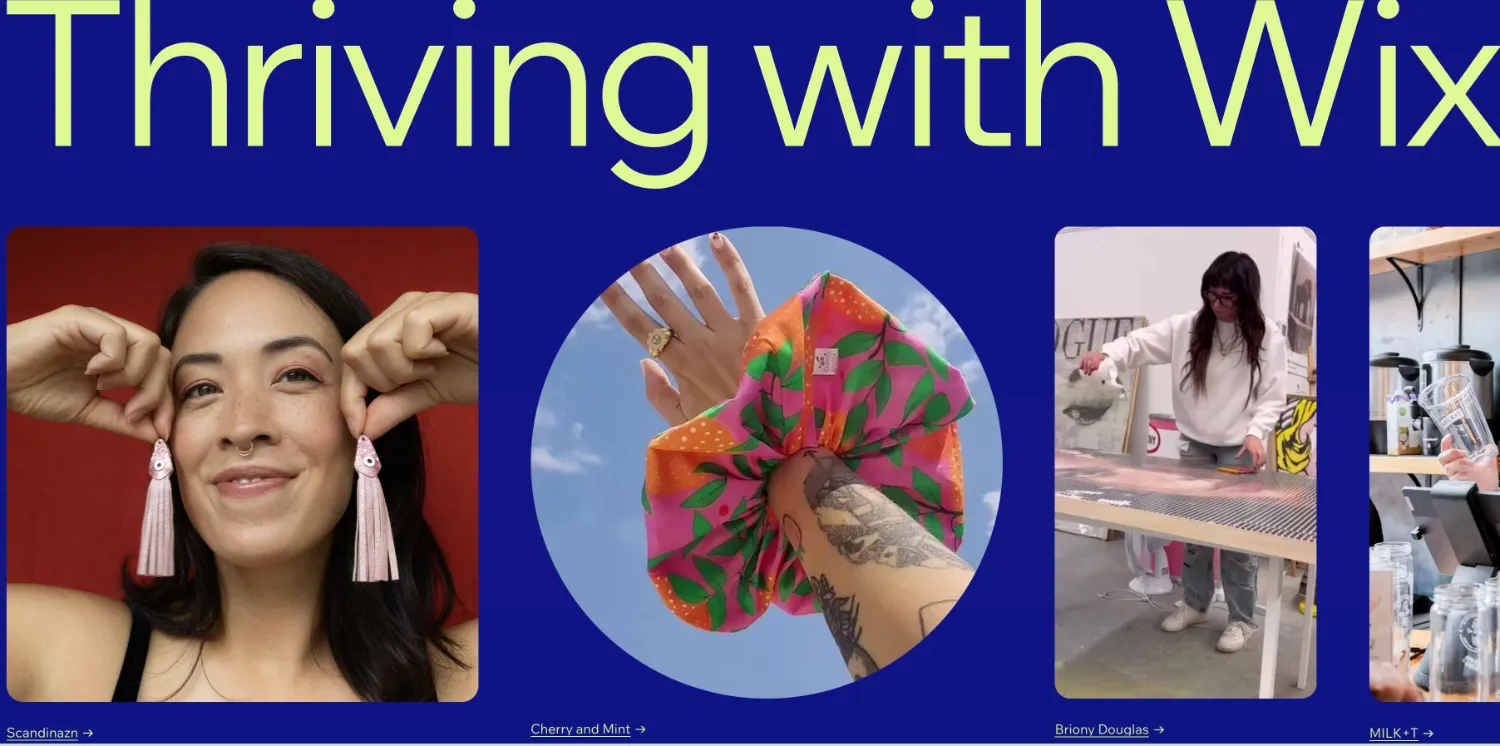
Wix 브랜드 및 디자인 부사장 하깃 카우프만(Hagit Kaufman)은 “폰트는 웹사이트 디자인에서 매우 중요한 요소다. 이번 폰트 라이브러리 확장을 통해 창작자들이 시각적으로 뛰어나고 브랜드에 잘 맞는 웹사이트를 만들 수 있기를 기대한다. 모노타입과의 협업은 전 세계 사용자에게 전문적인 디자인 도구를 꾸준히 제공하겠다는 우리의 의지를 보여주는 사례다”라고 밝혔다.
모노타입 수석 폰트 크리에이티브 디렉터 찰스 닉스(Charles Nix)는 “적절한 폰트는 브랜드의 성격을 정확하게 전달하는 핵심 요소다. 이번 협업은 창작자들이 다양한 방식으로 자신을 표현할 수 있도록 돕기 위한 노력이다. Futura®와 Beatrice를 비롯한 엄선된 폰트들은 사용자들이 원하는 디지털 이미지를 구현하는 데 큰 도움이 될 것이다”라고 전했다.